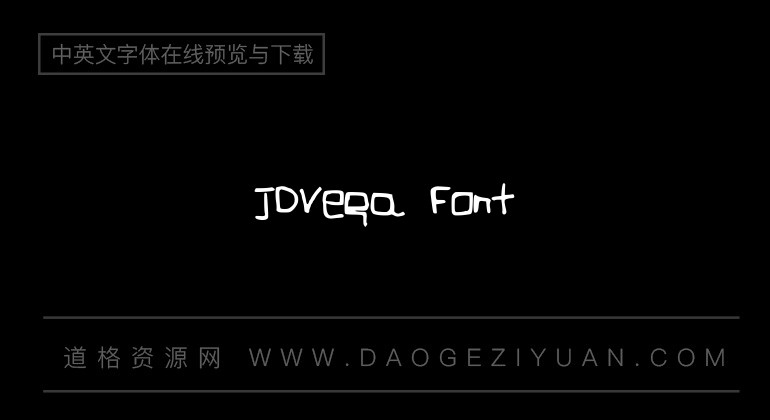
JDVega Font 是一款设计独特的字体,具有现代感和艺术气息。该字体的设计灵感来自于卡通和漫画,因此它的形状和线条都非常流畅,同时也非常适合用于设计卡通、漫画、广告、标志和海报等相关内容。 JDVega Font 字体拥有多种字重和风格,包括常规、斜体、粗体、粗斜体等等,可以满足设计师和创意人士的不同需求。此外,该字体还支持多种语言,如英语、西班牙语、葡萄牙语、法语、德语等,可用于国际设计项目。 总的来说,JDVega Font 字体是一款非常实用和具有创意的字体,可以用于各种设计和创意项目中,为你的作品增添独特的魅力。内容介绍
JDVega Font是一款非常不错的手写艺术字体,具有很好的视觉感,适合于文化类的宣传设计、商业类品牌的广告和产品包装设计以及个性化文字排版等较多场景。